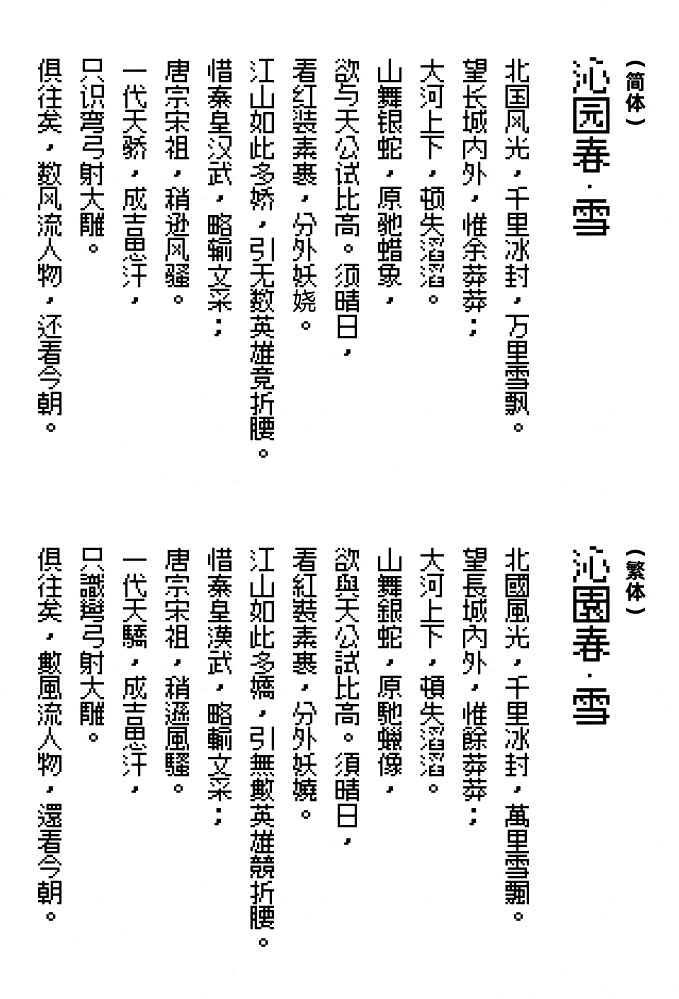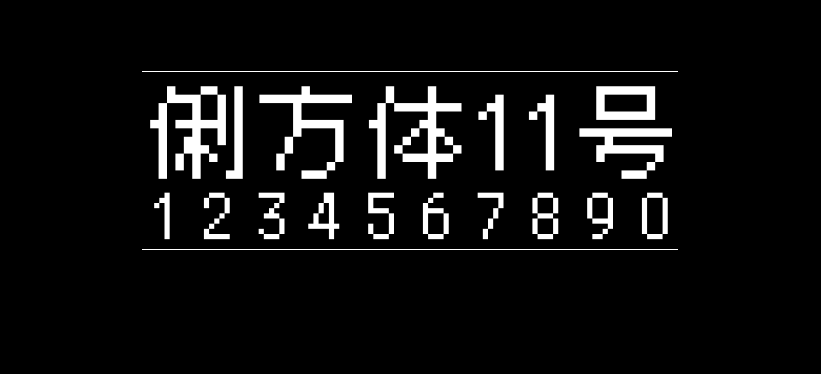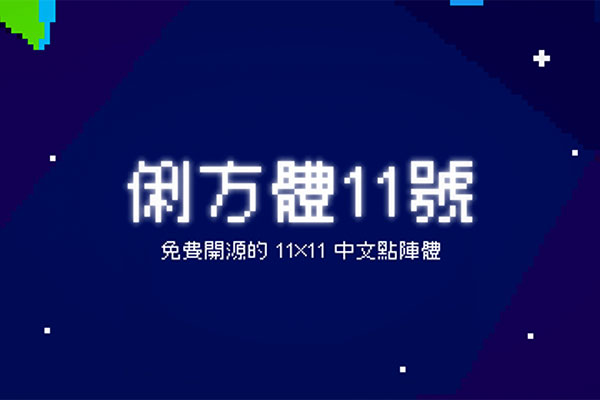
俐方体11号
俐方体11号(俐方體11号 / Cubic 11)的作者是中国台湾的ACh,以日文字型 M⁺ gothic 12r 为基础替繁体中文进行修改与扩充,其中包括适用繁体中文的标点符号以及较符合台湾地区习惯的字形等,可用于像素风格的游戏以及美术当中。
俐方体11号包含常用国字标准字体 4808 字、Big5 第一字面 5401 字、IICore 台湾常用字 T1A、T2A 及部分 T2B、台客闽粤字、注音符号、GB 2312 Level-1、通用规范汉字表一级、元素週期表之所有元素字符。俐方体11号对繁体的支持非常到位,简体字形支持得也不错。